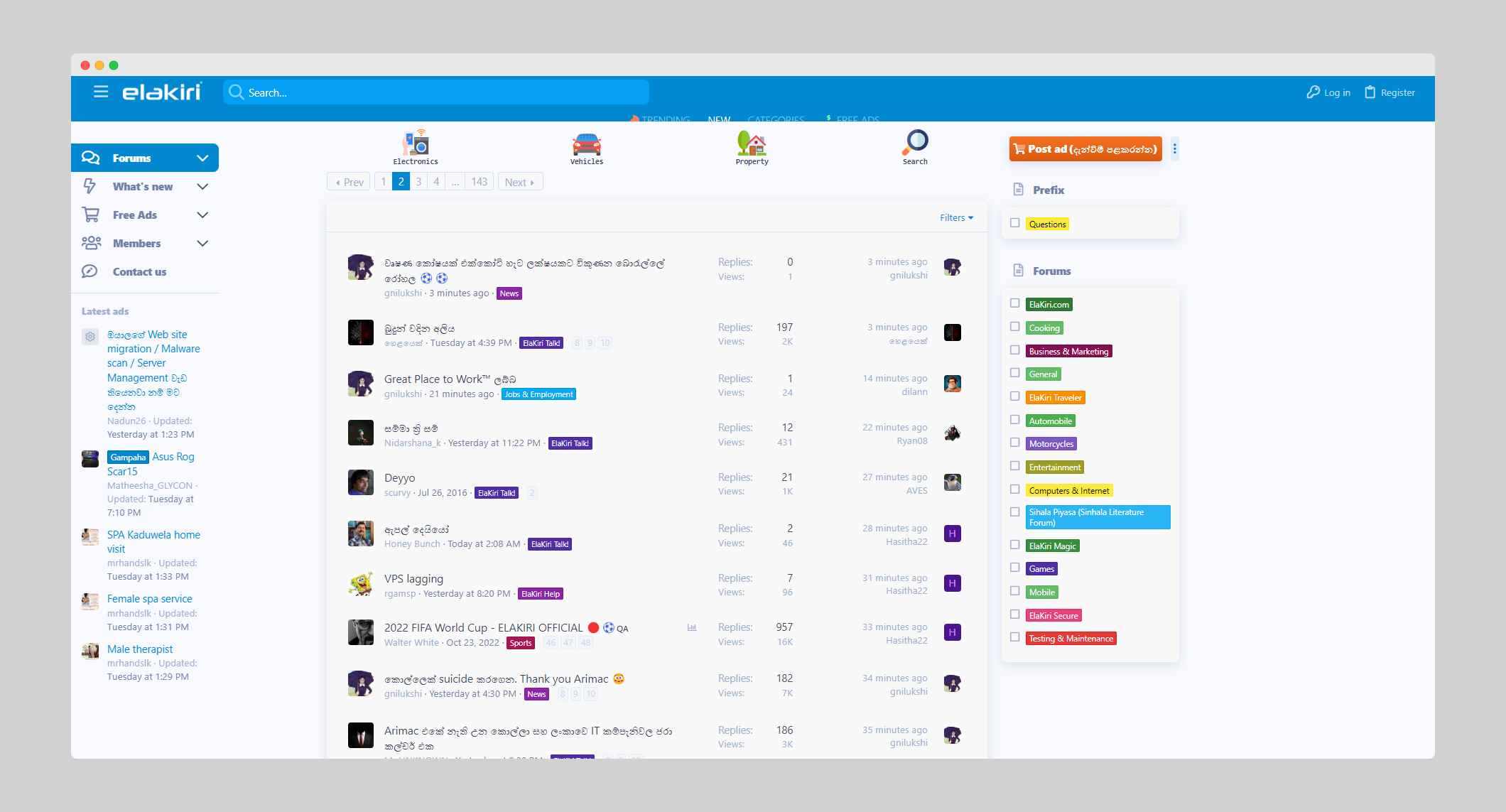
Windows 11 Sinhala Font đŸĨ´
āˇƒāˇ’āļ‚⎄āļŊ Keyboard āļ‘āļšāļšāˇŠ āļ¯āˇāļąāˇŠāļą āļœāˇ’⎄⎒āļąāˇŠ āļšāˇ™āļŊ āļ‹āļąāˇ.... āļ¸āˇšāļš āˇ„āļ¯āˇāļœāļąāˇŠāļą āļļ⎐āļģ⎒āļ¯ ?
Nirmala UI āļ¯āˇāļœāˇ™āļą āļ‰āļąāˇŠāļąāˇš Brave āļ‘āļšāˇš.. āļ’ āļ‹āļąāˇāļ§ System āļ‘āļšāļ§ āˇ€āˇāļ§āˇ’āļŊāˇ āļąāˇāˇ„⎐..
āļ‘⎄⎙āļ¸ āļ´āˇ™āļąāˇŠāļąāˇš āļšāˇ”āļģ⎔āļ¸āˇ’āļĢ⎒ āļ…āļšāˇ”āļģ⎔.. āļ†āļē⎚ āļ…āļģ āļļāˇāļŊ ⎀āļœāˇš āˇƒāˇ’āļ‚⎄āļŊ āˇ†āˇœāļąāˇŠāļ§āˇŠ āļ‘āļš āļœāˇœāļ¯āļœāˇāļąāˇŠāļą āļļ⎐āļģ⎒āļ¯ ?
Delete iskoola pota font from windows font folder. Restart the pc. Auto Nirmala UI walata windows reset wenawa.
āļ‹āļļ āļ‰āˇƒāˇŠāļšāˇāļŊāļ´āˇœāļ­ āˇ†āˇœāļąāˇŠāļ§āˇŠ āļ‘āļš āļ¯āˇāļœāˇ™āļąāļ¯ āļ‰āļąāˇŠāļąāˇ™ āļļāļŊāļ´āļąāˇŠ. C:;/Windows /fontsāļ’āļš āļ‘āļšāļ§ āļœāˇ’⎄⎒āļąāˇŠ āļ…āļē⎒āļąāˇŠ āļšāļģāļŊāˇrestart āļšāļģāļ´āļąāˇŠ. āļ‘āļ­āļšāˇœāļ§ āļ­āˇ’āļļ⎊āļļāˇ ⎀āļœāˇšāļ¸ āļ…āļšāˇ–āļģ⎔ āļŊ⎜āļšāˇ”⎀āļ§ āļ´āˇšāļąāˇ€āˇ.